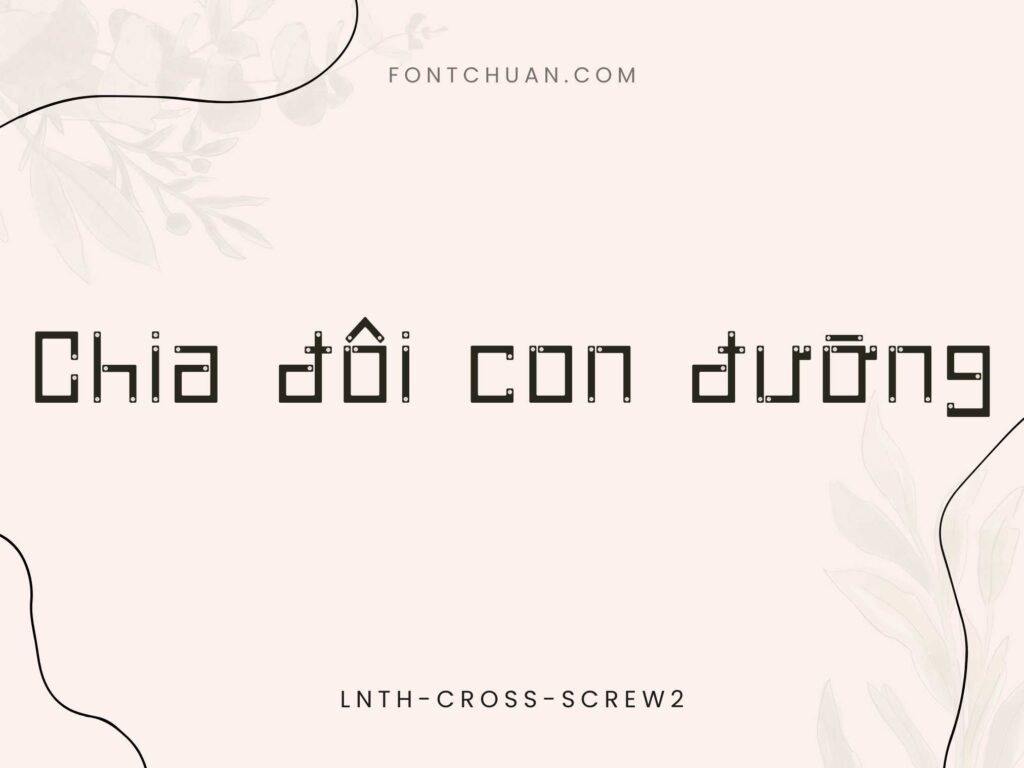
Font LNTH Cross Screw Việt Hóa
Tác giả Font: Fadly Baidowy
Cross Screw là một phông chữ độc đáo, mang phong cách thiết kế mạnh mẽ và cá tính, đồng thời chịu ảnh hưởng từ Font Gothic với các đường nét sắc sảo, góc cạnh và cấu trúc chữ mạnh mẽ. Phông chữ này tạo nên sự ấn tượng đặc biệt cho các dự án thiết kế, từ logo, poster đến bìa sách và các ấn phẩm quảng cáo. Nhờ được Việt hóa bởi LNTH, Cross Screw hỗ trợ đầy đủ các ký tự tiếng Việt, giúp người dùng dễ dàng áp dụng trong các dự án đa ngôn ngữ. Phông chữ này đã được sưu tầm và đăng tải bởi thành viên của Font Chuẩn, đáp ứng nhu cầu đa dạng của cộng đồng thiết kế.
Về đặc điểm thiết kế, Cross Screw sở hữu các ký tự được thiết kế tỉ mỉ, mang lại cảm giác mạnh mẽ và hiện đại. Phông chữ này đặc biệt phù hợp cho các dự án như thiết kế logo, poster, bìa sách và các ấn phẩm quảng cáo, nơi cần sự nổi bật và thu hút sự chú ý. Ngoài ra, Cross Screw cũng thích hợp cho các sự kiện như lễ hội, sinh nhật, Halloween và Trung thu, mang lại không khí sôi động và độc đáo. Trong lĩnh vực ngành nghề, phông chữ này được ứng dụng rộng rãi trong quảng cáo, thiết kế thiệp cưới, giáo dục và công nghệ, góp phần tạo nên sự khác biệt và ấn tượng cho các sản phẩm và thương hiệu.